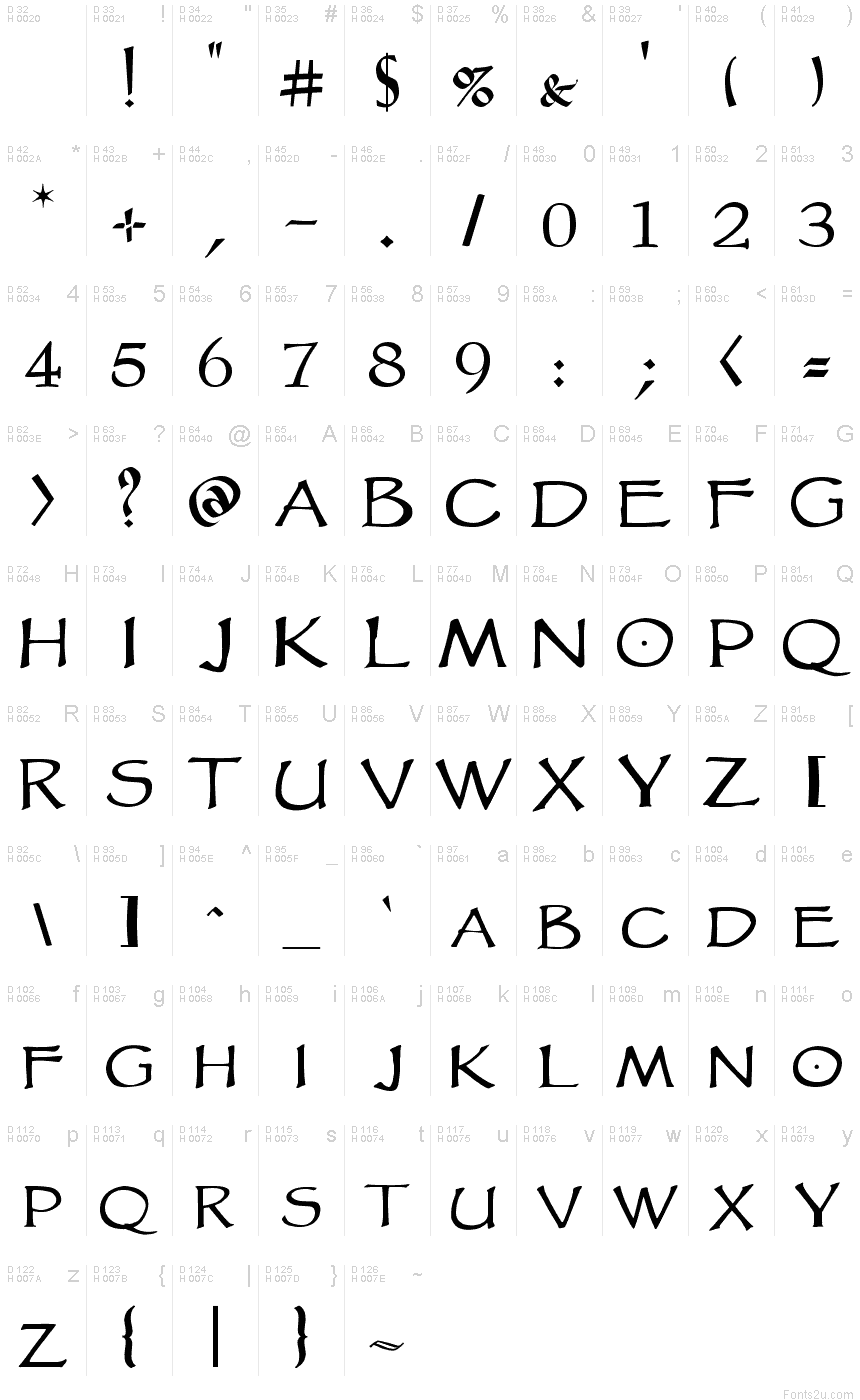
VTC Goblin Hand SC di VTC Vigilante Typeface Corporation è un font display gratuito in stile retrò con una sfumatura gotica da libro di fiabe. Le lettere sembrano disegnate a mano ma solenni, mescolando forme alte e svasate con caratteri più tondeggianti che si incurvano verso l'interno, terminando in piccole punte a uncino; la O puntinata conferisce al set un accento astuto, quasi da talismano.
Questo font gratuito è perfetto per progetti che richiamano un'atmosfera da fiaba antica senza scadere nell'horror: titoli di poster, copertine di libri, loghi di videogiochi, insegne di pub ed eventi grafici sono l'ideale. Si presta bene anche per brevi titoli, cartelli e monogrammi, poiché le maiuscole hanno dettagli abbastanza particolari da catturare l'attenzione, anche in poche lettere.